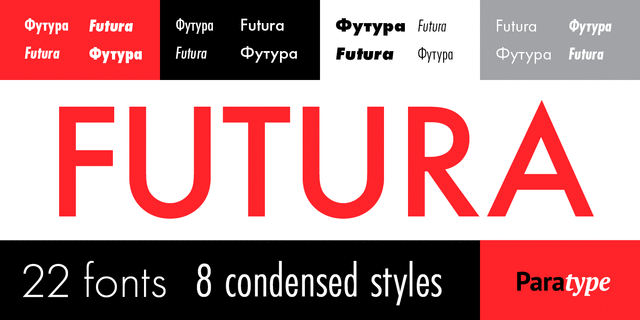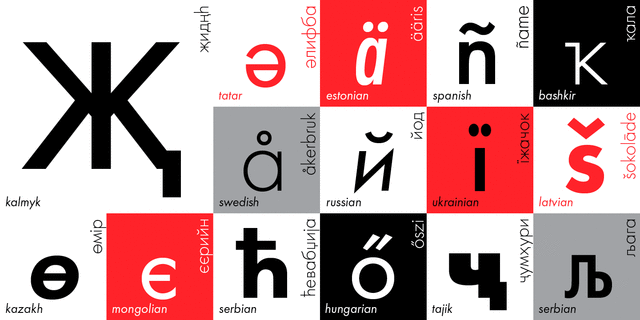
Футура разработана для фирмы Bauersche Giesserei (Bauer) в 1927 году (дизайнер Пауль Реннер). Этот гротеск, основанный на простых геометрических формах, навеян эстетикой конструктивизма немецкой школы дизайна 20—30-х годов Баухауз. Выпущенная фирмой Bauer в широком ассортименте начертаний различной насыщенности, Футура – один из самых популярных шрифтов как для текстового, так и для акцидентного набора. Первоначальная кириллическая версия в 8 начертаниях разработана в компании ПараТайп (ПараГраф) в 1995 году (дизайнер Владимир Ефимов). Дополнительные кириллические начертания разработаны в 2007 году Изабеллой Чаевой. Одновременно были частично перерисованы старые начертания. Теперь новая Футура представляет собой единую шрифтовую систему из 14 нормальных и 8 узких начертаний, согласованных между собой по стилю, метрикам и насыщенности для совместного применения. Futura является зарегистрированной торговой маркой Bauer Types.
Ассоциации c начертанием Futura PT HeavyКачества и характер:
городской, строгий, мотивирующий, чертежный, инженерный, понятный, глобализированный, глобалистичный, архитектурный, умный, современный
Особенности семейства Futura PTХит десятилетия:
Хит 1930-х Хит 1980-х Хит 2010-х Этот шрифт в логотипах:
Nike, Absolut Vodka, House MD, Ikea, Hewlett-Packard, Earthlings, Charite
Близкий исторический оригинал: